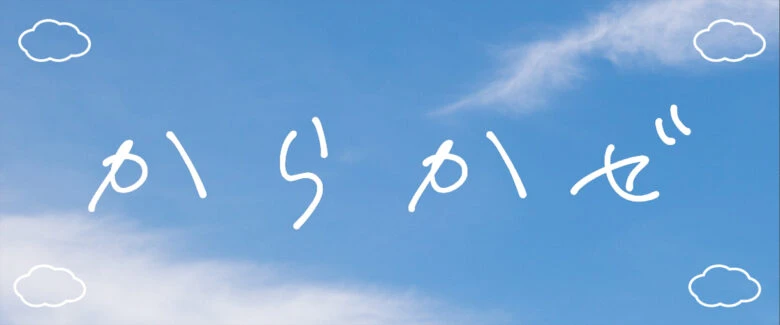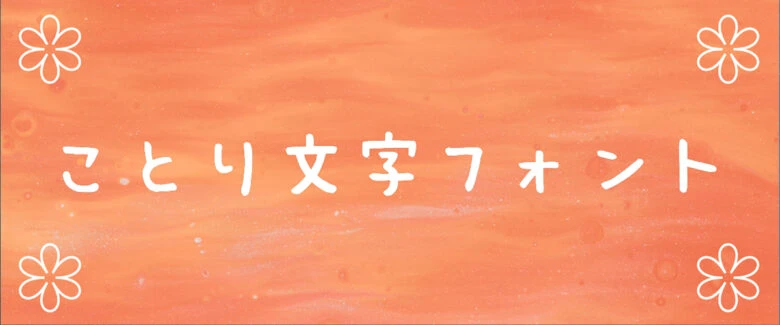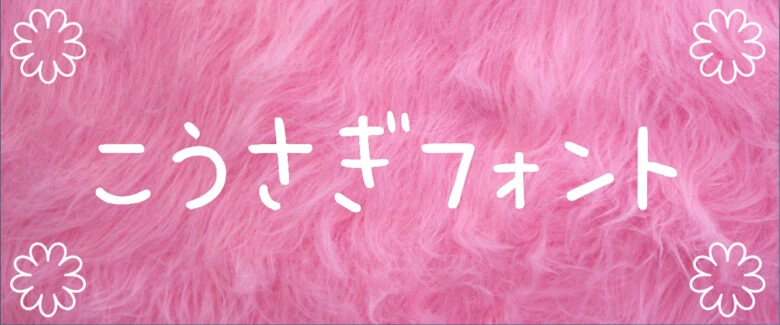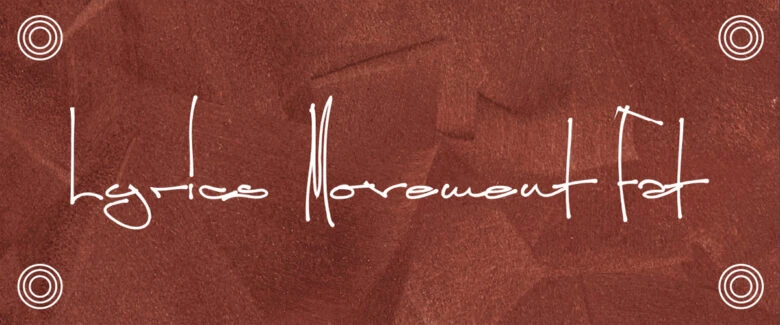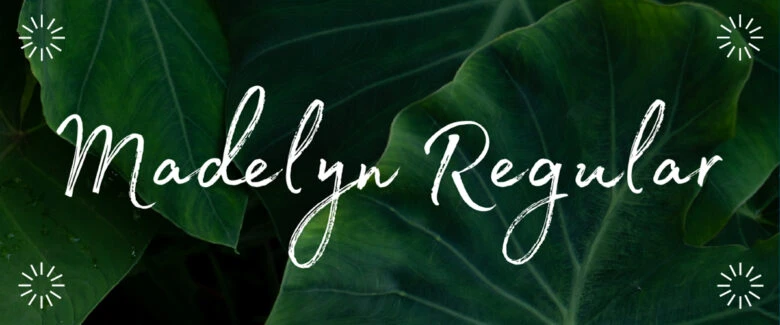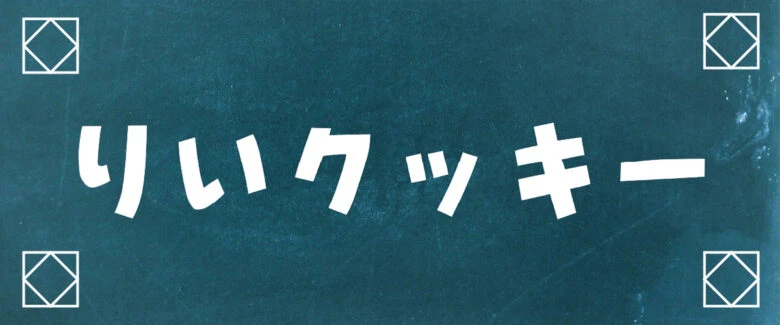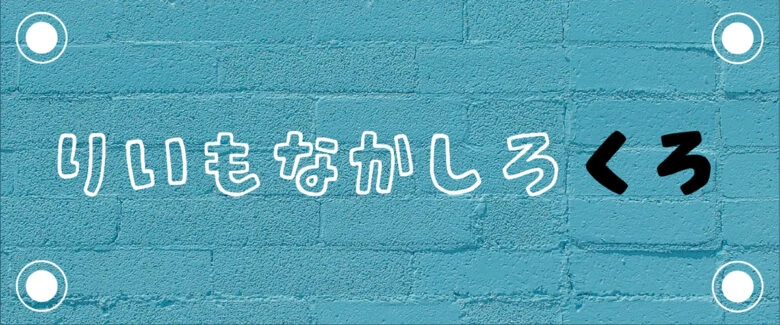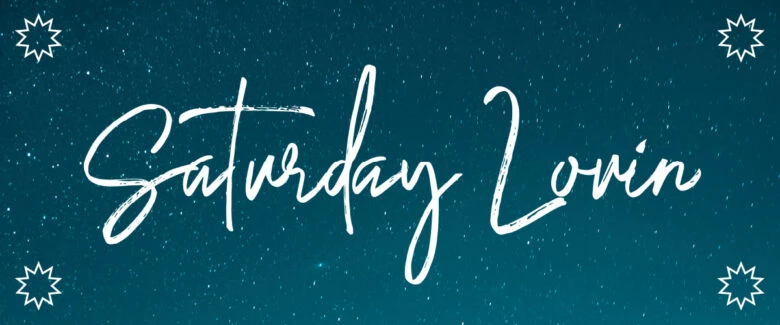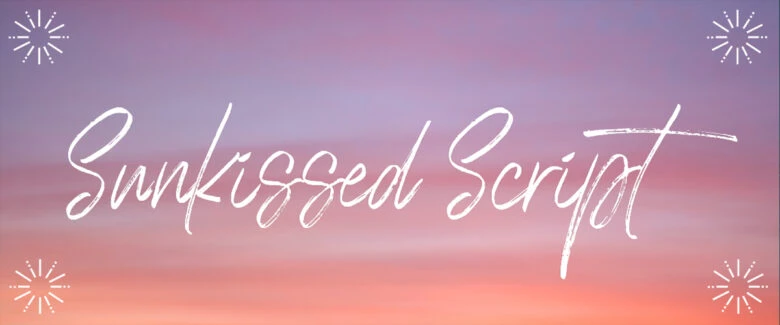
手書きのようなフォント(字体・書体)で書かれているキャッチコピーや文章。デザイン性の高い手書き風フォントは、優しさや親しみやすさが伝わるだけではなく、遊び心や面白さを表現するときにもオススメで、さまざまなシーンで効果を発揮します。
本記事では、Picsartオススメのおしゃれな手書きフォントを紹介するとともに、フォント選びのコツや手書きフォントの効果なども併せてご紹介!
フォント選びのポイントと注意点
どのようなデザインも、複数の要素を組み合わせてメッセージを伝えますが、中でも大切な要素のひとつが「文字のフォント」です。
フォントは視覚的な要素が強く、デザインの質や効果を大きく左右します。そのため、フォントを選ぶ際は「見やすさ」「伝わりやすさ」「読みやすさ」の3つを意識することが重要です。
フォントの見やすさ
パッと見た時に文字だと認識できることが大切です。文字が潰れてしまったり、背景色や画像と重なってしまったりするものはNGです。フォント選びと同時に、文字のサイズ・行間・字間を調節しましょう。
フォントの伝わりやすさ
文字の区別が明確であれば、メッセージをしっかりと伝えることができます。漢字の「土と士」、英字と数字の「Oと0」など、一瞬で識別できるフォントを選びましょう。
フォントの読みやすさ
情報を伝えることが目的である資料やLP(ランディングページ)は、スラスラと読みやすい文章が必須です。その場合、見出しとそれに続く文章を別のフォントにしたり、文章中の目立たせたい箇所のフォントや大きさ、色、濃淡を変えたりなど工夫しましょう。
注意を引くことが目的である場合、読みやすさをあえて無視することもあります。デザインをする際は、制作物の目的やデザインの意図をしっかりと見据えたうえでフォントを選ぶとよいでしょう。
手書き風フォントの効果
とてもユニークな手書き風フォント。ゴシック体や明朝体にはない、親しみやすさを読み手に与えます。
ここでは、手書き風フォントの効果や手書き風フォントを使うメリットをご紹介します。
手書き風フォントの効果1. メッセージ性の強さ
手書き風フォントの1番の強みは、メッセージを伝える強さではないでしょうか。手書き風フォントを使えば、伝えたい想いをダイレクトに伝えられます。
年賀状をはじめとした手紙類にも最適で、特に感謝や感傷的なメッセージを届けたいときに効果的です。売り手の想いを伝えながら販売するセールスレターやチラシでは、強調部分に手書き風フォントを使用するとよいでしょう。
また、写真に手書き風フォントでメッセージを書いたフォトレターは、読み手に感情移入や共感を生むはずです。
手書き風フォントの効果2. 親しみやすさ、柔らかさを表現
文字を書く機会が減っている現在では、手書き文字を見るとどことなく懐かしさを感じるようです。
人の手で書いたような手書き風フォントは、温かみがあり、親しみやすく柔らかい印象を与えます。そのため、温もりや穏やかさを届けるなら手書きフォントがオススメ!ユーザーに共感を与え、興味を高めるデザインに仕上がるでしょう。
手書き風フォントの効果 3. 個性的な作品を創造できる
手書き風フォントは、ポップさやオリジナリティを高め、デザインに特別感を生み出します。個性を押し出したい作品には、正にオススメのフォントといえるでしょう。
Picsartの手書き風フォント一覧(日本語版)
ここでは、日本語の手書き風フォントをご紹介します!
からかぜ
走り書きしたようなフリーフォントは、冬の空気のような乾いたニュアンスを持っています。文字ごとに独特の個性を解き放っており、少し大人っぽい手書き風フォントが使いたい方にオススメです!
uuuuube(有料)
少し遊び心のある手書き風フォント。あたたかいスウィートな文章をちょっぴりクールに仕上げます。
りいクッキー(有料)
紙に書いた文字から作られた手書き風のかなフォント。角がカクカクしているものの、全体的に丸さを帯びているため、ほんわかとしたイメージを与えることができます。
りいもなかしろ/りいもなかくろ(有料)
角が丸く、袋文字の「しろ」と、黒ベタ文字の「くろ」があります。面白さやおかしさ、ユニークさを強調したいときにもオススメです!
こうさぎフォント(有料)
カフェメニューや黒板の手書き文字をヒントに作られた手書き風フォント。サイズが微妙に不揃いなところや、文字の傾きがすべて一定ではない点が、遊び心をくすぐります。
ことり文字フォント
サインペンで書いたような小さめの手書き風フォント。丸い文字が手書きの味わいを強く引き出し、可愛らしさを強調しています。ハートフルな手紙に使うと想いがしっかりと伝わるでしょう。
Picsartの手書き風フォント一覧(英語版)
ここでは、Picsartの人気の手書き風フォント(英語版)をご紹介!
Saturday Lovin(有料)
走り書きしたような筆記体が印象的の手書き風フォント。手書きのクセを活かして、アルファベットの大小のバランスを上手に保っています。
Madelyn Regular(有料)
実際のフリーライティングの筆記体に基づいた手書き風フォントです。媚びないカジュアルな雰囲気で、親しみのある字体がどんなシーンにも活躍します。
Sunkissed Script(有料)
キュートでおしゃれな筆記体の手書き風フォントです。ロゴやポスター、グリーティングカードなどに使用しても可愛く仕上がるでしょう。
Lyrics Movement Fat(有料)
細めの線で書き上げて、一つひとつのアルファベットをコンパクトにおさめた手書き風フォントです。はかなさや淡い想いなどを表現するのに最適です。
Picsartの手書き風フォントで「想い」を伝えよう
手で書いたような印象を与える手書き風フォントを活用することで、フォントの視覚効果も相まり、オリジナリティ溢れたデザインに仕上げられます。
また、手書き風フォントはそれ自体が持つイメージがあるため、届けたいメッセージを視覚的に届けることが可能です。